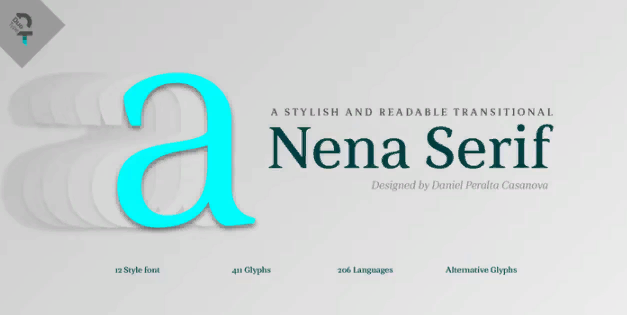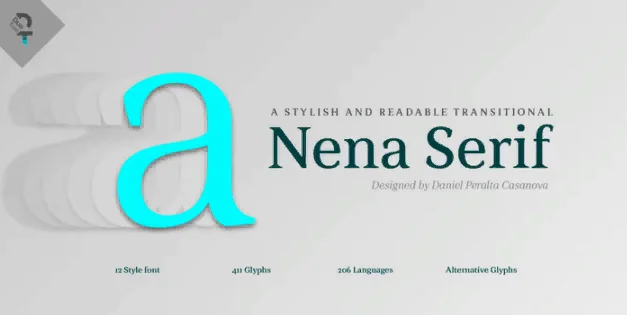
Nena Serif
- это переходный читаемый шрифт, выполненный в современном стиле и предназначенный для широкого чтения книг, газет и журналов. Шрифт очень хорошо читается при использовании в мелком основном тексте, со средней высотой x и умеренным контрастом создает элегантный вид на странице и хорошо подходит для стильных заголовков и различного экранного использования.
Шрифт Nena Serif доступен в 6 вариантах веса, от легкого до тяжелого, с соответствующим курсивом и альтернативными глифами. Шрифт содержит набор символов из 411 знаков, поддерживающих 206 различных языков.